儿童节海报专用手写字体
六一儿童节就要到了,还在纠结儿童节海报用字吗?字语坊推出一波手写字体,喜欢的设计师朋友们可前往字体视界下载哦。
银河杂货铺该字体是一款手写字体,字形纤细,笔画粗细一致。
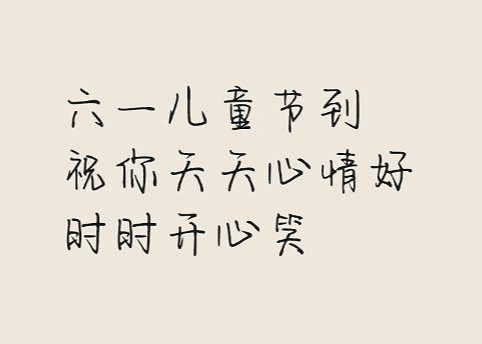
银河杂货铺
日系可爱奶酪体该字体是一款具有手写风格的卡通字体,字体乖巧可爱,适合很多年轻小伙伴们卖萌。
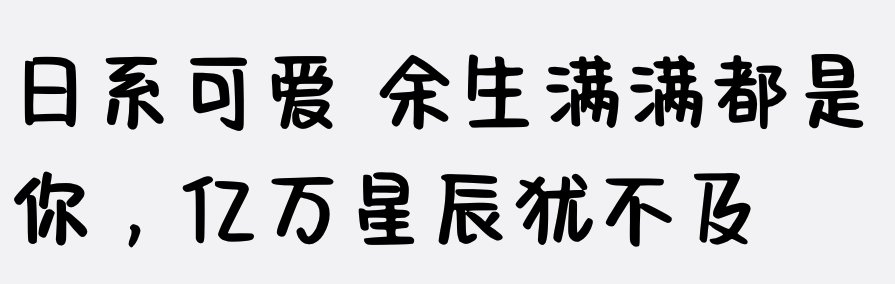
日系可爱奶酪体
你的记忆因我停留字体展现随性,并且笔画之间透出的可爱、随性,更为字体增添了几分魅力。
你的记忆因我停留